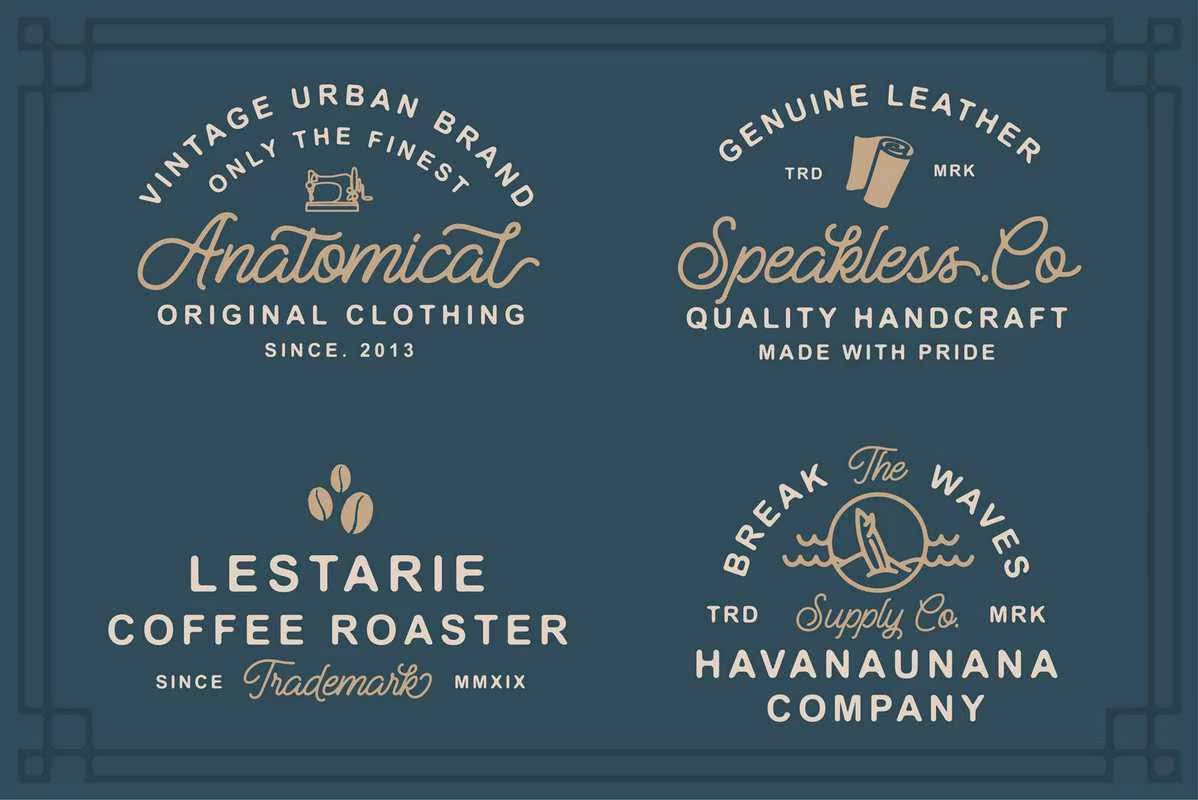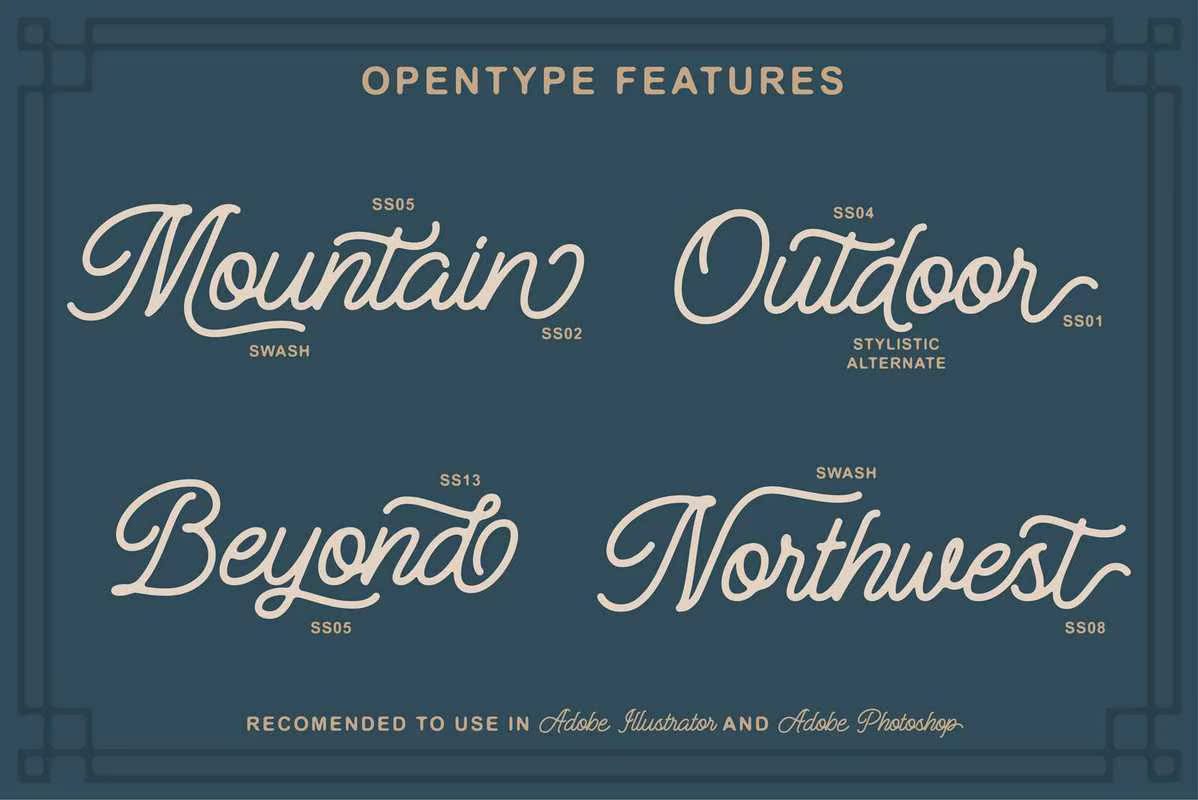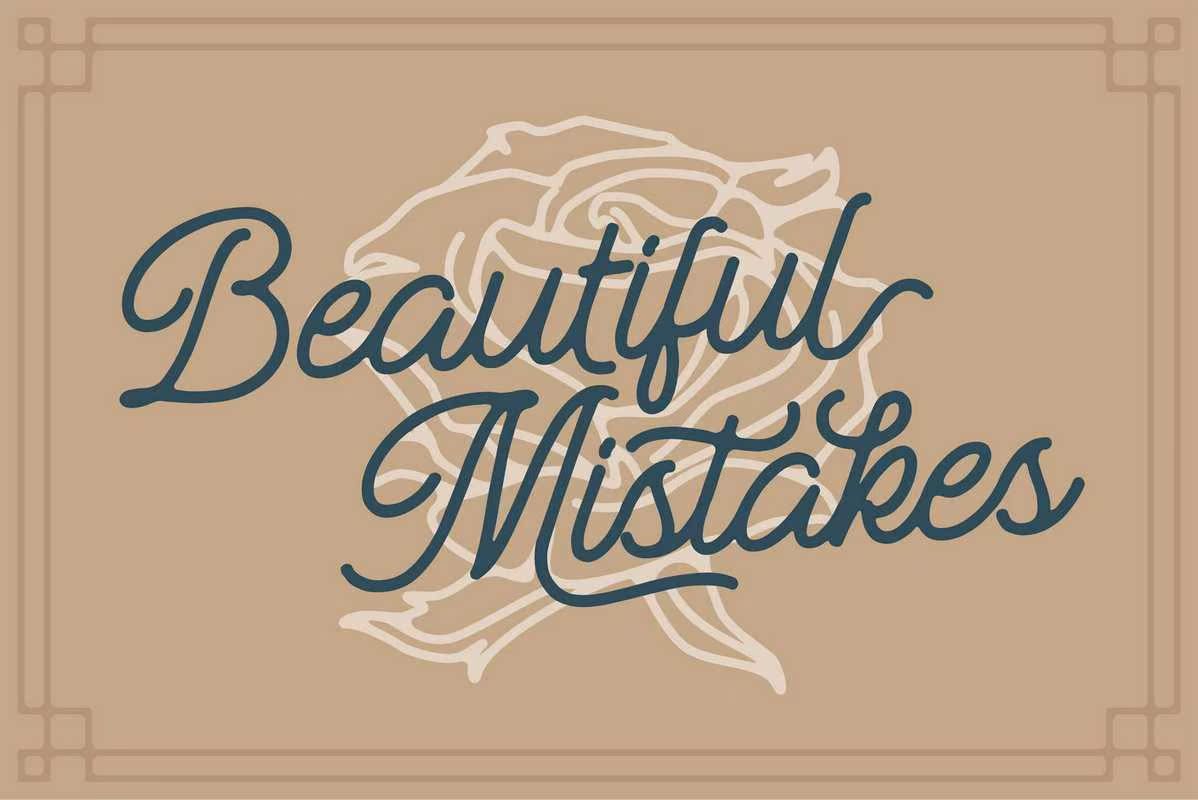
Introduction Maneman Monoline Scription Font.Inspired by Vintage Style Printing与Modern-Pography Style相结合。使用208字形替换包括Swash的OpenType功能。Introduction Maneman Monoline Scription Font.Inspired by Vintage Style Printing与Modern-Pography相结合。使用208字形替换包括Swash的OpenType功能。